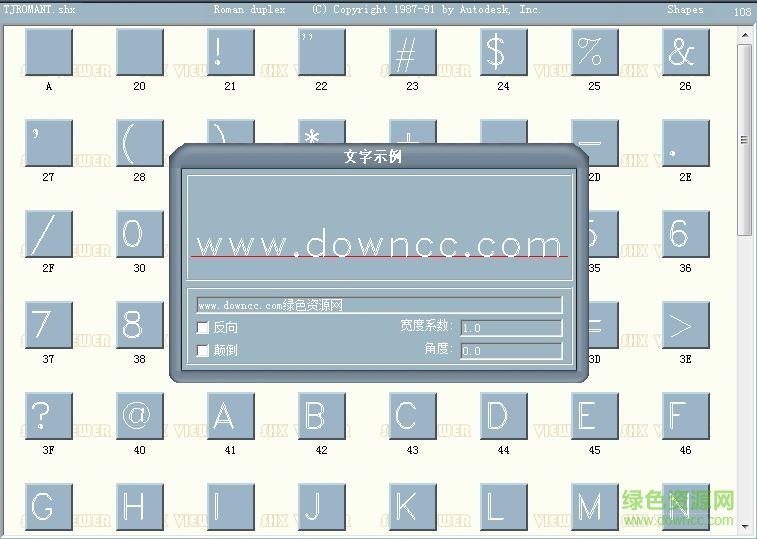
tjromant.shx字體的出現(xiàn)解決了在相關(guān)的工程制圖行業(yè)中的眾多制圖問題,讓你平時無法進行輸入的字符能夠通過這款字體文件進行調(diào)用與輸入,十分便捷,快來綠色資源網(wǎng)下載吧!
tjromant.shx在眾多cad字體中也能夠獲得最佳的使用效果,因為它的用途十分廣泛,在眾多行業(yè)中都需要輸入其內(nèi)的各類字符。
1、大字體是在CAD中由字母、數(shù)字、標(biāo)點符號和具有一定比例和外觀設(shè)計的符號構(gòu)成的字符集。是CAD獨有的一種線性字體,也就是通常所說的SHX字體
2、 SHX字體有g(shù)benor.shx、geniso.shx,大字體有hztxt.shx、gbcbig.shx等,一般各個公司和個人都有各自規(guī)定或喜愛的字體,因此也沒有特別的統(tǒng)一。